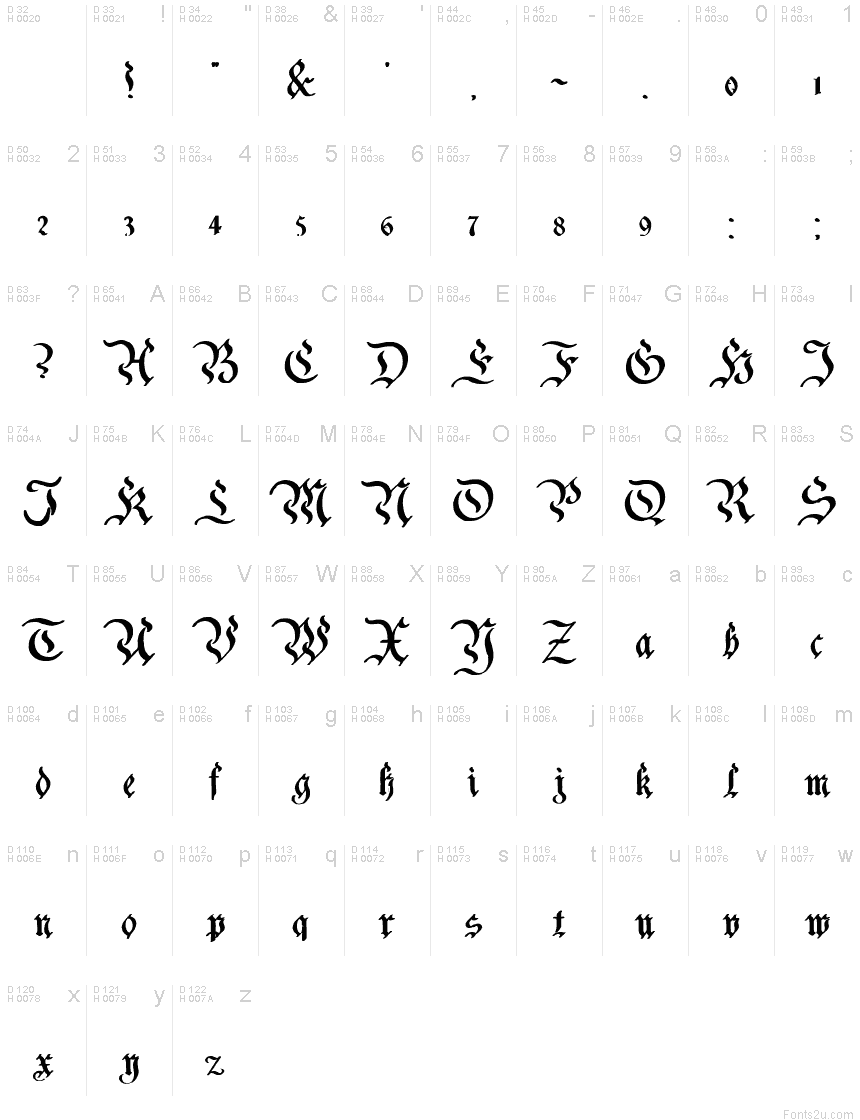
Charterwell Bold od PJL to darmowy, gotycki krój pisma nawiązujący do średniowiecza, o ciężkiej, niemal atramentowej prezencji i dramatycznym charakterze każdej krzywizny. Wysokie, przypominające płomienie wielkie litery oraz ciasno splecione małe litery sprawiają wrażenie wyjętych wprost z iluminowanego manuskryptu, jednak w znacznie mroczniejszym, bardziej agresywnym wydaniu. Gęste, czarne formy zazębiają się, nadając nagłówkom solidną, „wykuty w kamieniu” wagę, której nie da się pominąć.
Charterwell Bold pozwala nadać głęboko klimatyczny wyraz okładkom książek fantasy, logotypom metalowych zespołów, tytułom gier, plakatom w stylu dungeon-crawler, szyldom festiwalowym czy okultystycznym gadżetom. Rytm kresek tworzy wyrazistą teksturę, dlatego krój ten błyszczy zwłaszcza w większych rozmiarach, gdzie ostre haki i zamaszyste krzywizny mogą w pełni wybrzmieć. Połącz ten darmowy font z prostym, nowoczesnym bezszeryfowym krojem w tekście głównym, aby zachować czytelność układów, podczas gdy Charterwell Bold zajmie się budowaniem dramatycznego nastroju.